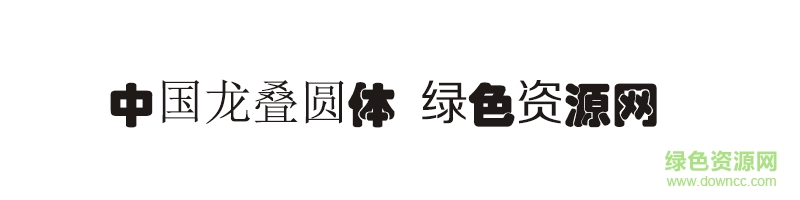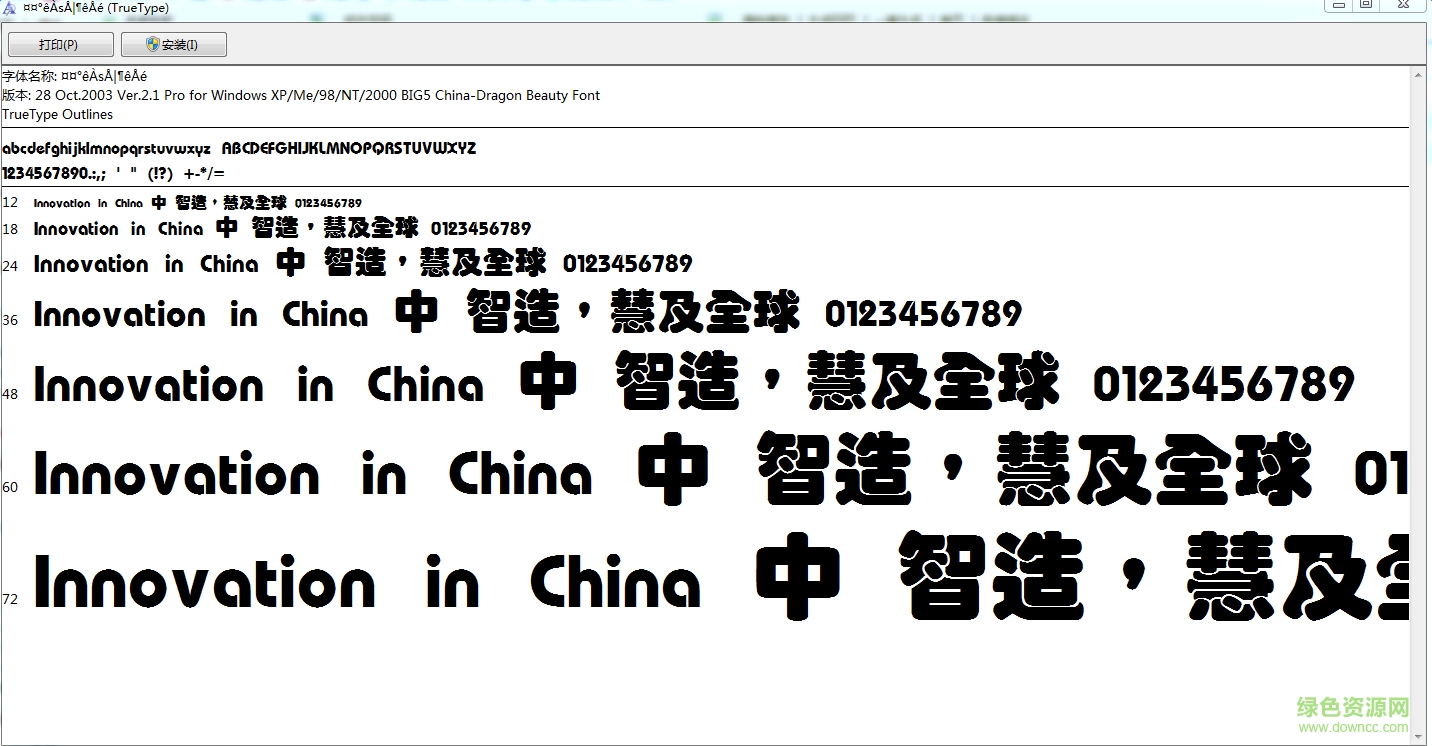
中國(guó)龍疊圓體字體是一款中國(guó)風(fēng)圓形字體軟件,字體工整好看,給人一種整體舒服的感覺(jué),沒(méi)有突出的尖角,非常圓滑,喜歡的朋友歡迎來(lái)綠色資源網(wǎng)下載體驗(yàn)!
在藝術(shù)設(shè)計(jì)和各種商業(yè)海報(bào)的制作中,字體的風(fēng)格選擇是十分重要的,不同的風(fēng)格字體都會(huì)造就不同的視覺(jué)效果。而中國(guó)龍疊圓體是一套充滿中國(guó)風(fēng)的中文字庫(kù),綠色資源網(wǎng)給大家提供好看的中國(guó)龍疊圓體字體!